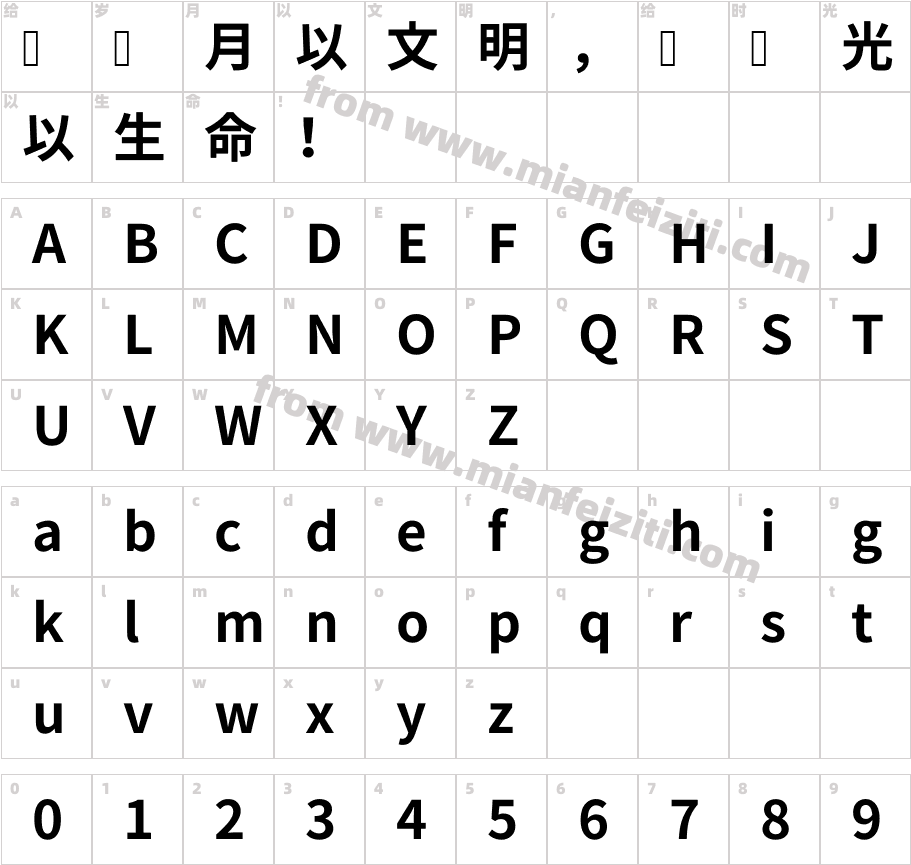
思源真黑-P-Bold
字体名称: 思源真黑-P-Bold
Postscript名称: GenShinGothic-P-Bold
字体版本: Version 1.002.20150607
字体品牌: 思源
本款“思源真黑-P-Bold”是一款书写很新颖的字体,字体大方,适合各种设计作品使用!欢迎下载!